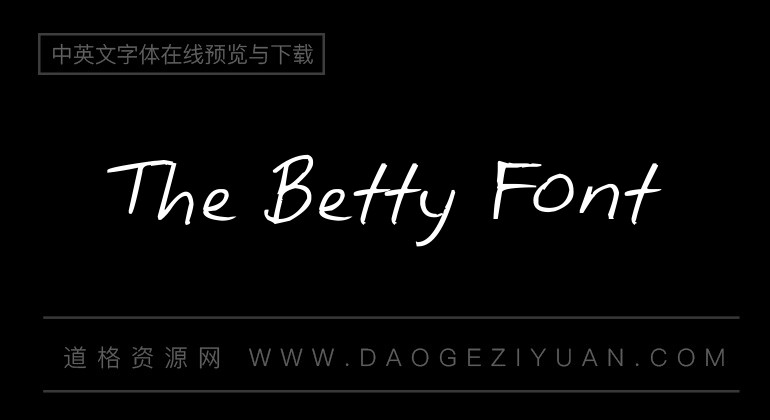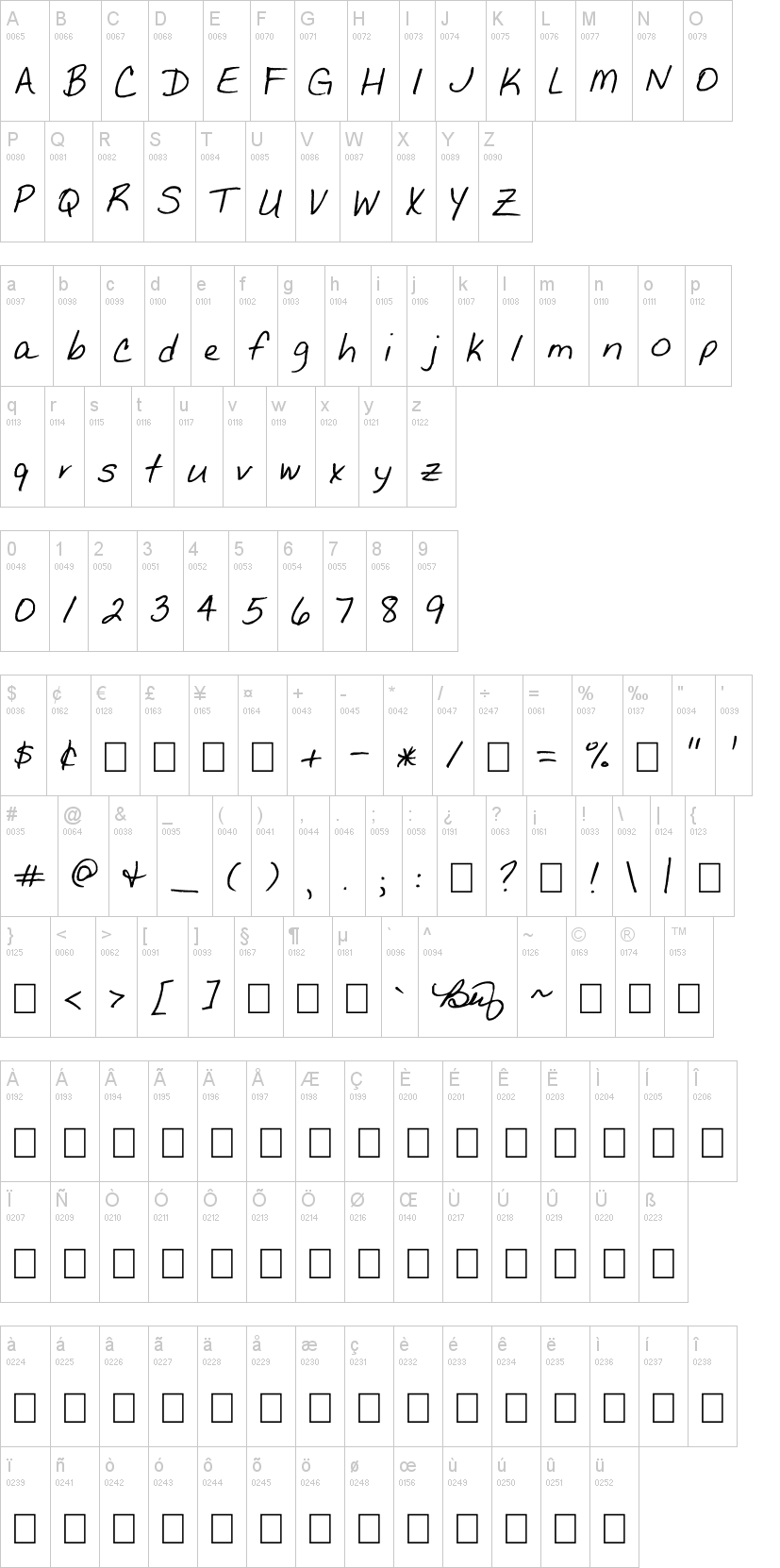
The Betty Font 是一款由 Blambot 公司设计的现代简约字体,它具有清晰的线条,精致的细节,以及简洁的外观。它的字体样式介于细体和粗体之间,适合在网页,印刷品,以及其他应用中使用。字体的特点是它的抗锯齿性,可以在任何分辨率下保持清晰的文字效果。另外,它的字体大小可以调节,从小到大,可以满足不同的使用需求。内容介绍
The Betty Font是一款非常不错的手写艺术字体,具有很好的视觉感,适合于文化类的宣传设计、商业类品牌的广告和产品包装设计以及个性化文字排版等较多场景。